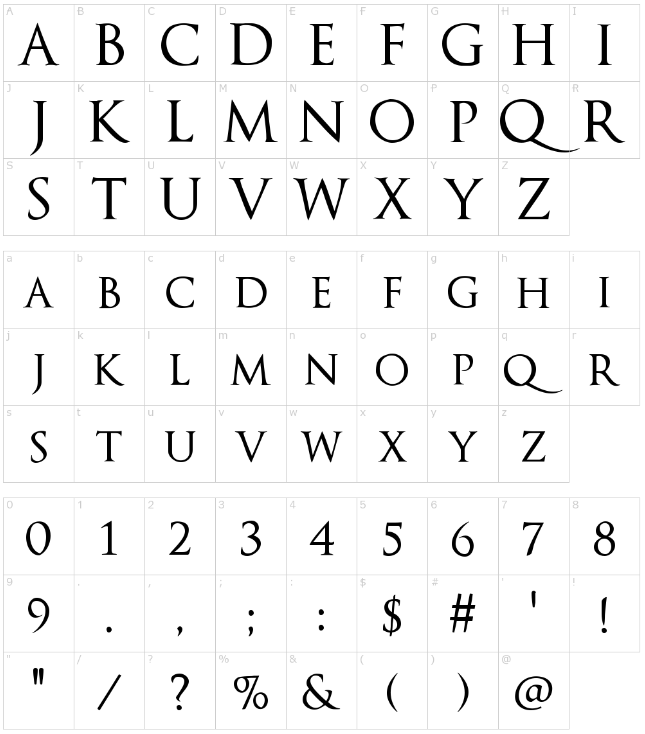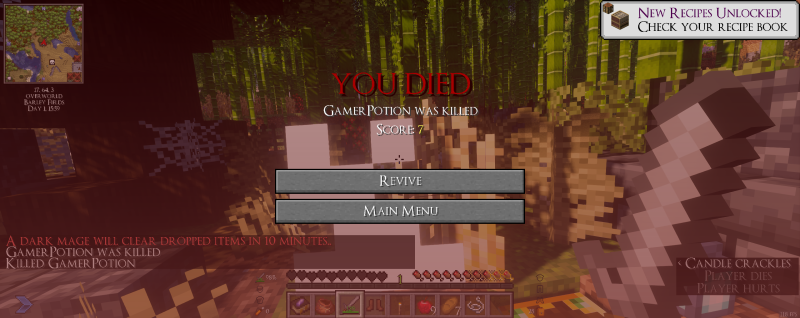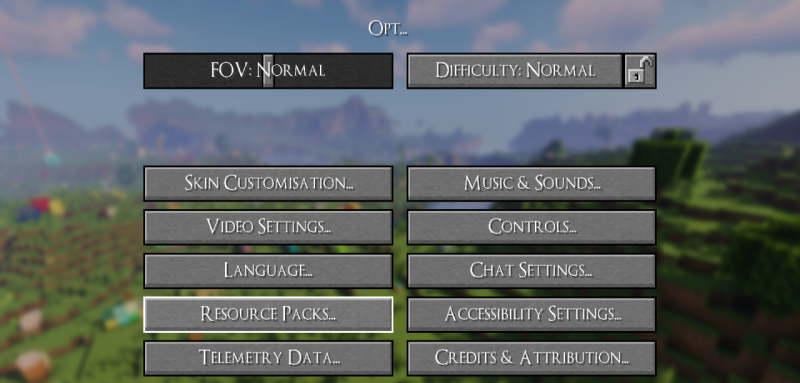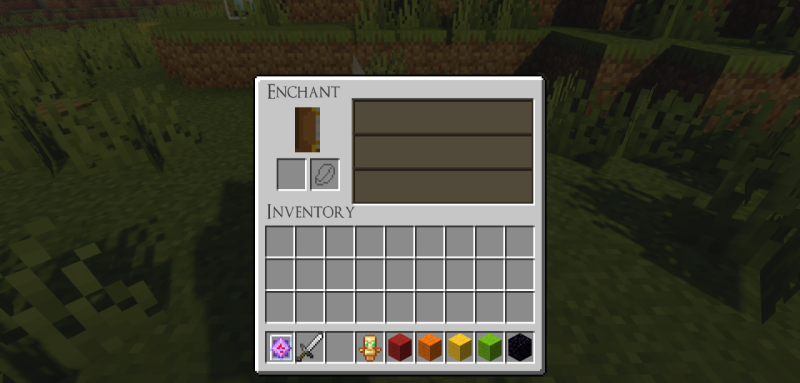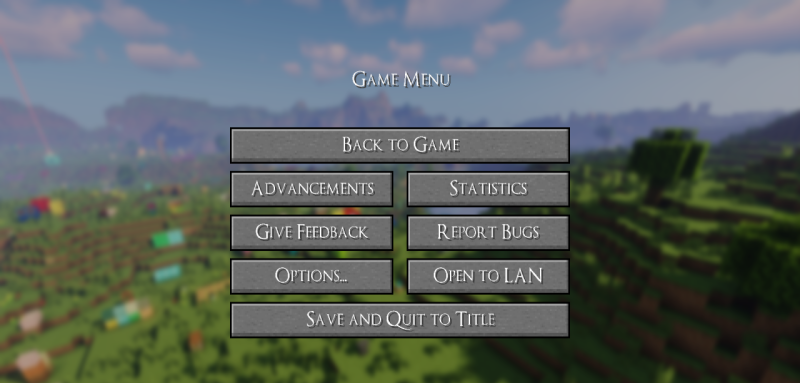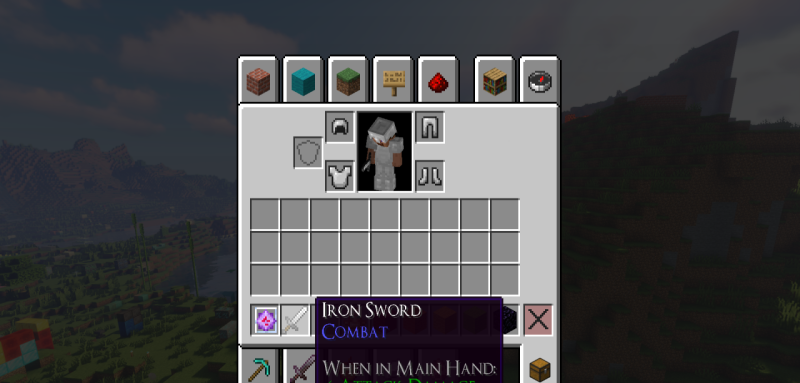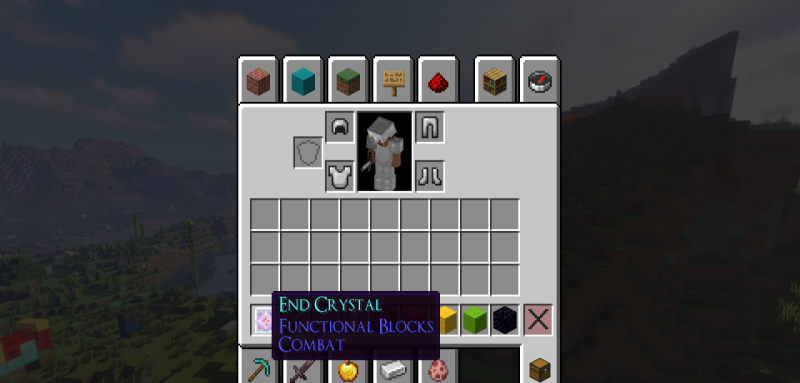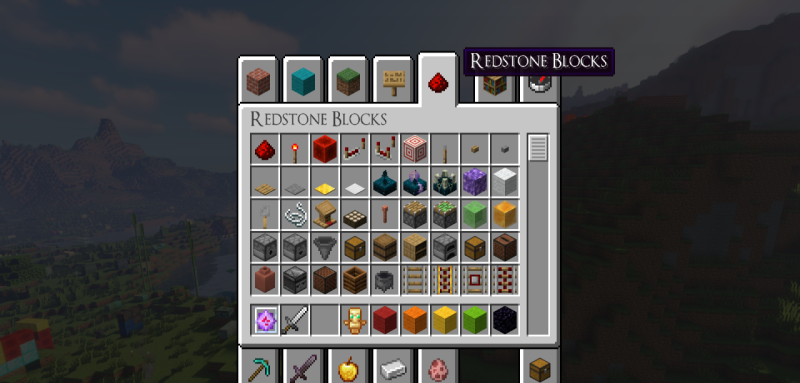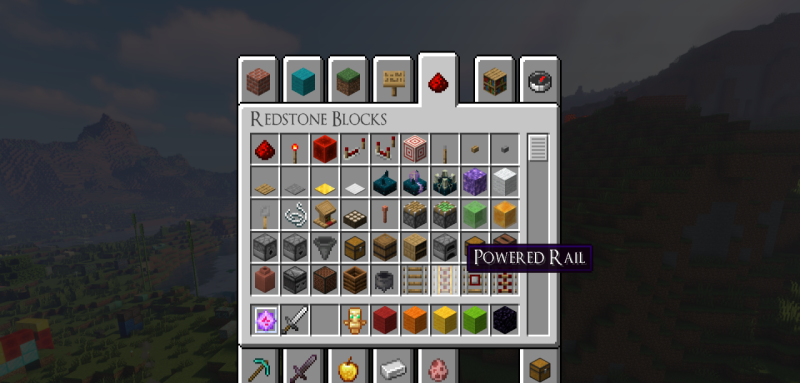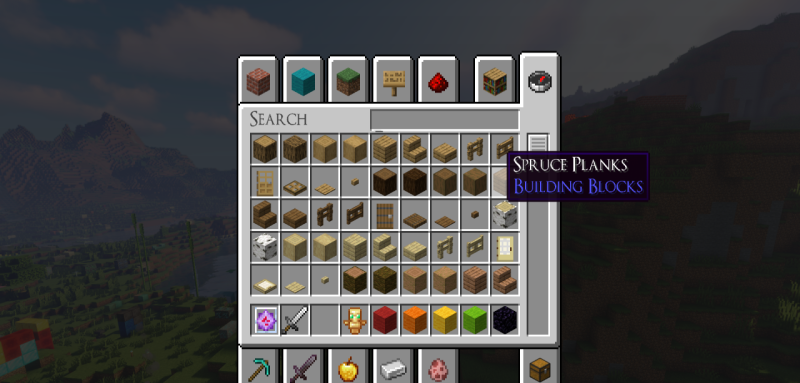
Souls RPG Font 26.3/1.21.11 (готический шрифт, RPG стиль 16x)
Текстурпак Souls RPG Font заменяет стандартный шрифт Minecraft на готический и средневековый, вдохновлённый популярной серией игр Dark Souls. Шрифт легко читается и отлично подходит для создания мрачной, RPG-атмосферы.
Основан на шрифте Optimus Princeps от Manfred Klein и распространяется по лицензии Free Font License. Изначально создавался для модпака DarkRPG, но теперь доступен всем желающим.